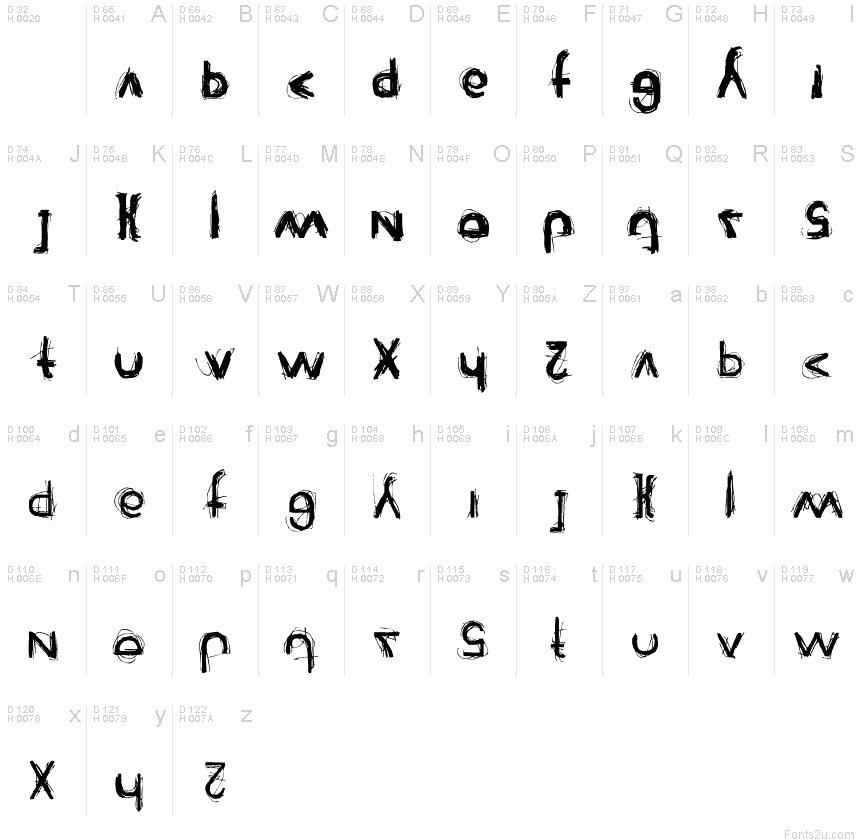
Reienhardt, di MatreroG Disenio, è un font trash gratuito con un ritmo grezzo e incisivo. Le lettere sembrano graffiate da un pennello asciutto e un pennarello in conflitto tra loro; il mix di bordi irregolari, punte improvvise e forme circolari sciolte conferisce alla scritta un aspetto nervoso e urbano.
È ideale per flyer di club, copertine di fanzine, poster punk, copertine di dischi e titoli dove la texture deve avere lo stesso peso delle parole. Come font gratuito per titoli brevi, nomi di band o citazioni d'impatto, regala un tocco inquieto e "di strada", perfetto per layout veloci e un branding volutamente imperfetto.